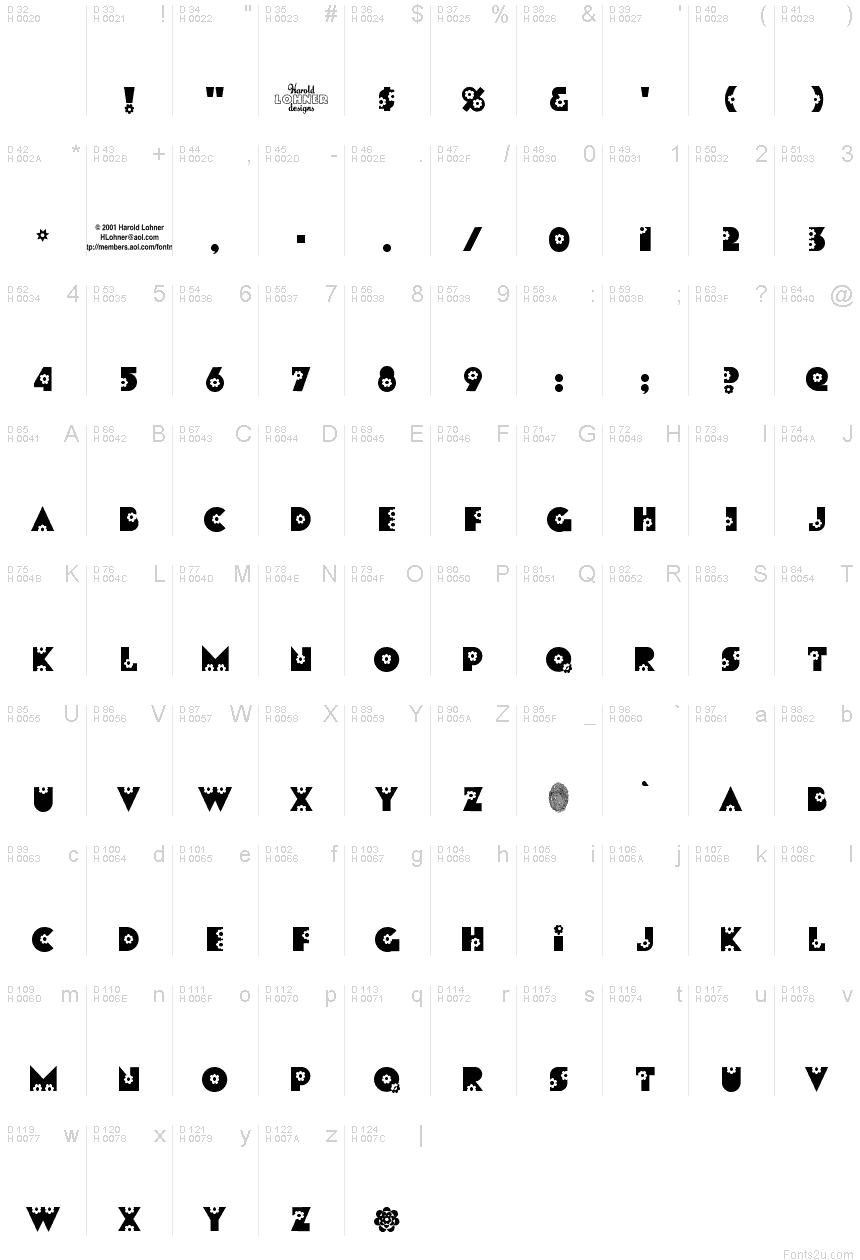
Flores od Harolda Lohnera je bezplatné dekorativní titulkové písmo, které promění každé písmeno v odvážný prvek zdobený okvětními lístky. Masivní, plakátové tvary působí, jako by byly vystřižené z matného papíru, zatímco ostré bílé květinové výřezy vystupují jako nálepky na tmavém pozadí. Písmo je inspirováno vývěsním štítem květinářství ve španělské Valencii a vyzařuje slunnou energii pouličního trhu, která okamžitě evokuje čerstvé květiny, teplý vzduch a ručně malované výlohy.
S písmem Flores váš text nejen promlouvá – on září. Tento bezplatný font skvěle vynikne na plakátech k jarním akcím, v logách květinářství či zahradnictví, na blahopřáních, pozvánkách na dětské oslavy, hravých obalech i veselé grafice na sociální sítě. Používejte jej ve větší velikosti, aby květinové detaily zůstaly jasné a čitelné, a zkombinujte jej s jednoduchým geometrickým bezpatkovým písmem, aby byl celkový vzhled moderní a přehledný.